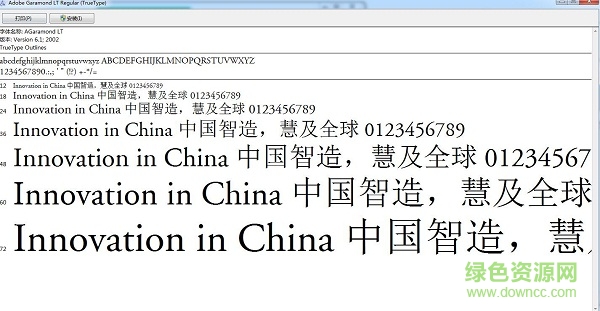
agaramondlt bold/regular
agaramondlt-bold和agaramondlt regular兩款襯線字體是綠色資源網(wǎng)為需要的朋友整體的免費(fèi)合集包,這套字體流暢干凈,起筆和收筆十分分明,穩(wěn)定實(shí)用,歡迎大家下載體驗(yàn)!
agaramond字體推薦
agaramondlt bold